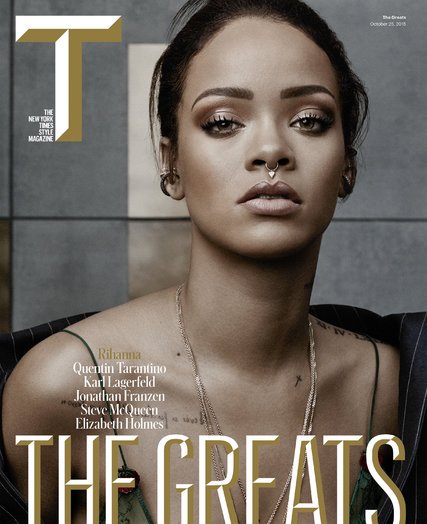
Wie heißt diese Schriftart?
ich durchkämme bereits seit Tagen das Internet nach dieser Schriftart:
Habe alle Geometrischen Schriftarten durchsucht und kann sie trotzdem nicht finden.
Auf der Netzseite des Magazins verwendet man die „Graphik X Cond Web Semibold Regular“. Nun kann man die „Graphik“ hier erwerben, eine „X Cond“-Version sah ich da aber nicht und auch keine Zierversion wie man sie auf der Titelseite verwendet. Ev. wurden diese speziell für das T-Magazin erstellt.
Schade, ich bin mir sicher, dass es diese Schriftart irgendwo gibt.
Sie wurde auch schon mal in einem Imagefilm von einem anderen Unternehmen verwendet.
Das ist mit großer Sicherheit eine Exklusivschrift, die von Commercial Type (Christian Schwartz) für die New York Times entworfen wurde.
Geht es dir explizit um diese Schrift oder lediglich um den 3D-Effekt?
Ja genau, es geht um den 3D Effekt.
Klar, es kann ruhig eine ähnliche Schriftart sein.
eine sehr ähnliche Schrift, und einer der ältesten Anwendungen kenne ich von dieser Vorkriegs-Benzinmarke:
Soch eine Schrift darzusellen ist aber in der normalen Schrifttechnik mit nur einem Font schwierig. Hier gibt es 3 unterschiedliche Ansätze:
1. die Hintergrund und die Schattenfarbe sind auf 2 unabhängige Font - und dann noch einmal in der Schattens aufgeteilt, beide Fonts haben dann identische Metrics und im Grafikprogramm muss dann  der Techt zwei mal exakt übereinanderiegend geschrieben sein, zu unterst mit dem Hintergrund-Font - in deinem Beispiel in weiß, hier in rot, und dann exakt da drüber in dem Schatten-Font und der Schatten-Farbe.
In Grafik- und D-Programmen ist das gut umsetzbar, in gängiger Textverarbeitung aber recht schwierig.
2. Ein weg, den ich schon für einen anders gestalteten Font gegangen bin, der den Effekt dann auch in normalen Textverarbeitungen einsetzbar macht: Hier habe ich die Grundform der Buchstaben (also hier die Hintergrundform) auf die Großbuchstaben gelegt, den buchstaben aber keine Breite gegeben, sosass die Einfügemarke an der Stelle bleibt, und die 2. Farbe der Buchstaben auf die Kleinbuchstaben gelegt. Hier muss man dann den Text so zuerst mit einer anderen Schrift schreiben: (am beispiel Leuna) LlEeUuNnAa, den Kleinbuchstaben dann die Schattenfarbe zuweisen und dann dem Text den ASpezialfont zuweisen. Ich glaube aber nicht, dass es schon einen solchen Schatteneffekt-Font in dieser Technik gibt, da dies ein quasi privates Experiment von mir war.
3. Eine neuere Technik, mit der auch solche farbigen Fonts möglich werden, die eigentlich für Emoticons auf modernen Touch-Betriebssystemen ersonnen wurde. Hier hat leider wieder jeder Betriebssystem-Hersteller sein eigenes Süppchen gekocht, und die Weiterentwicklung der Truetype-Technik funktioniert leider derzeit nur am Windows8 aufwärts. Auch wäre bei dieser Technik dann die Vordergrund-  und Hintergrundfarbe vorgegeben.